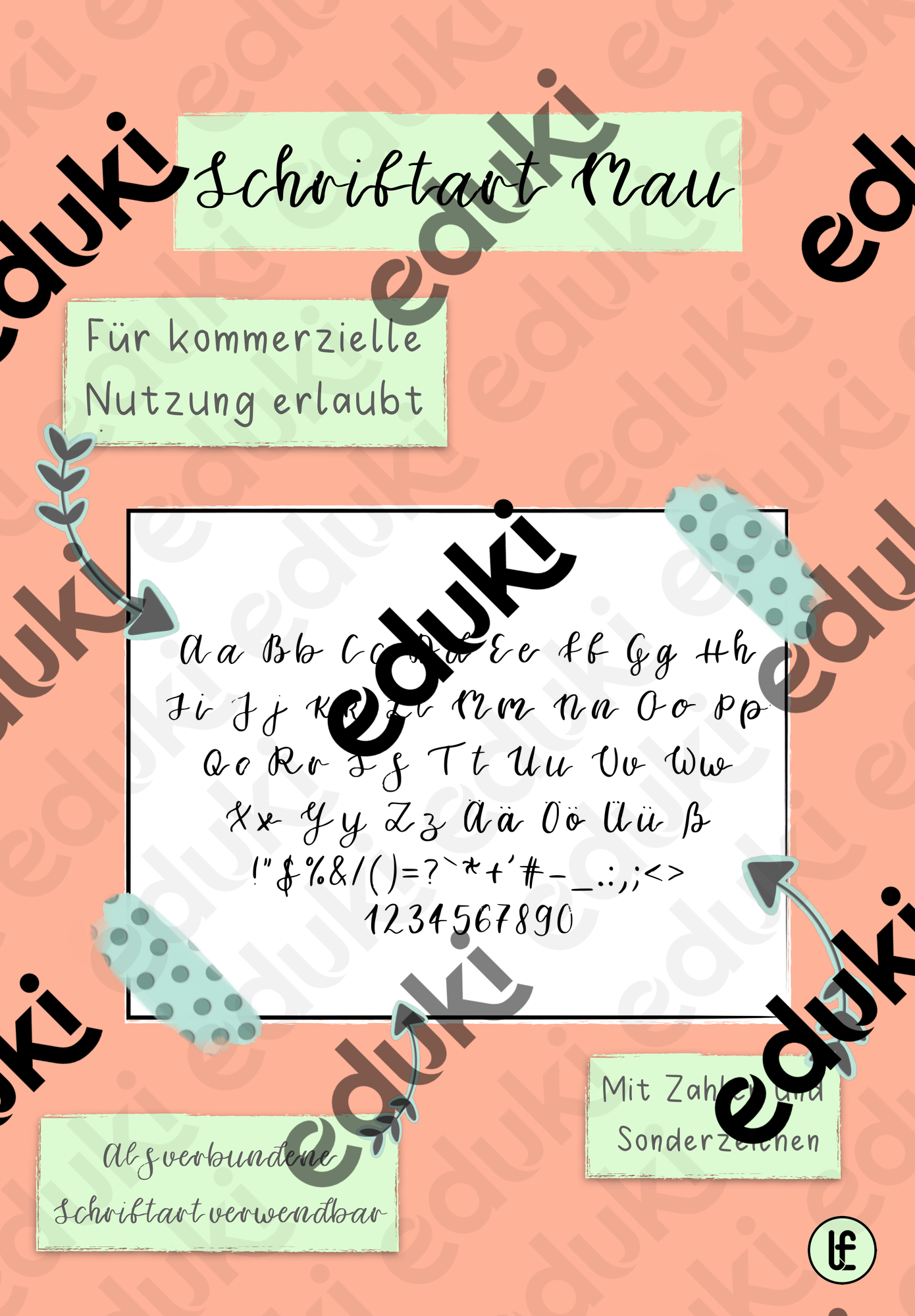
selbst erstellte Schriftarten - Schriftart "Mau" by @lehrerin.franzi - Deckblatt
Das Material umfasst eine selbsterstellte Schriftart. Sie ist weder eine Druck-, noch eine Schreibschrift und dient der kreativen Gestaltung.
Die Schrift ist perfekt um deinem Material, deinen Nachrichten uvm. einen individuellen Touch zu geben.
Schriftart "Mau" by @lehrerin.franzi